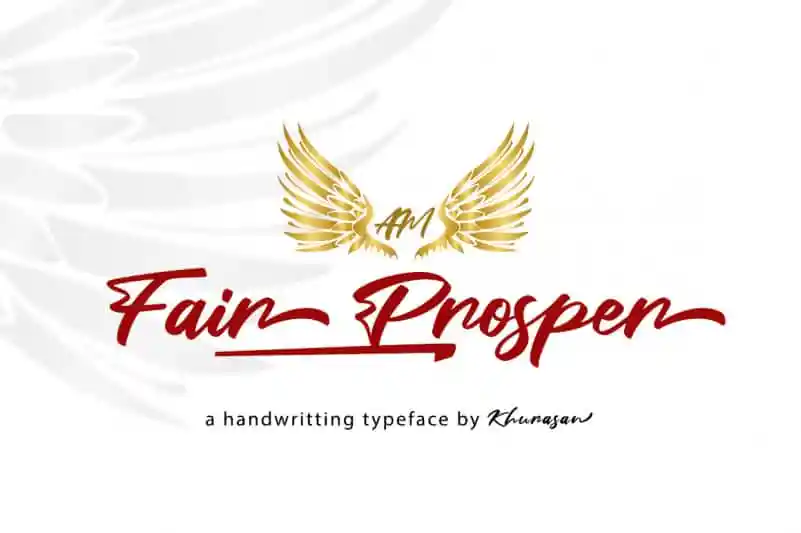
Fair Prosper Script Font – Download Grátis
A Fair Prosper Script Font é uma fonte script com estilo bold que transmite tanto um caráter sério quanto um tom descontraído. Esta elegante fonte é perfeitamente adequada para aplicação em branding, design de logotipo, lettering, embalagens, revistas, editoriais e materiais promocionais como panfletos, sacolas de shopping e camisas. Ela se adapta perfeitamente a uma variedade de projetos gráficos, incluindo retratos e eventos especiais. Se você está buscando um toque único para seus trabalhos de design ou até mesmo para expressar seu estilo de escrita pessoal, esta fonte é perfeita. Ela transmite confiança e originalidade ao mesmo tempo em que oferece uma aparência sofisticada e moderna. Com a Fair Prosper Script Font, você terá todas as ferramentas necessárias para adicionar um toque autêntico à sua próxima produção gráfica.